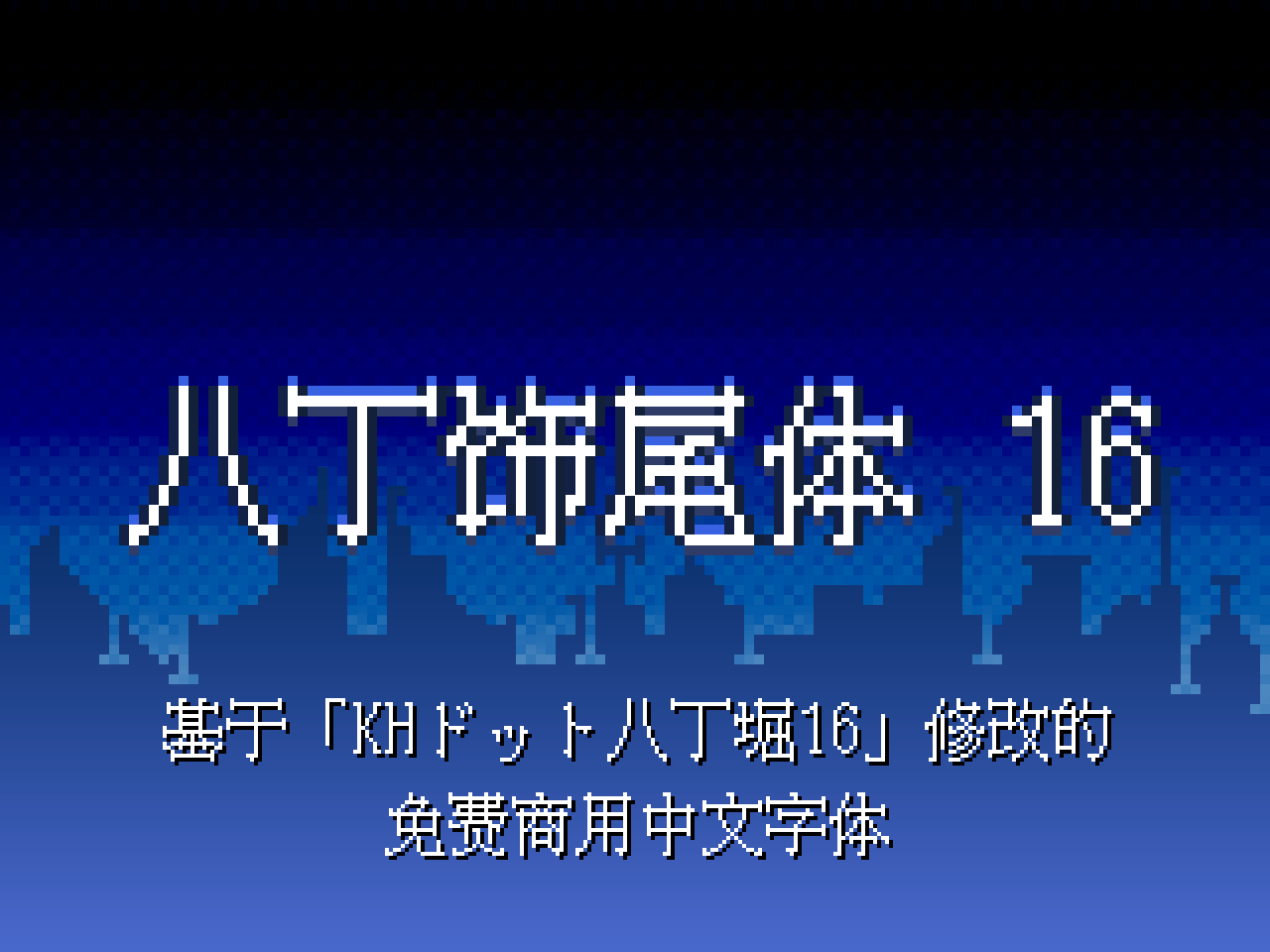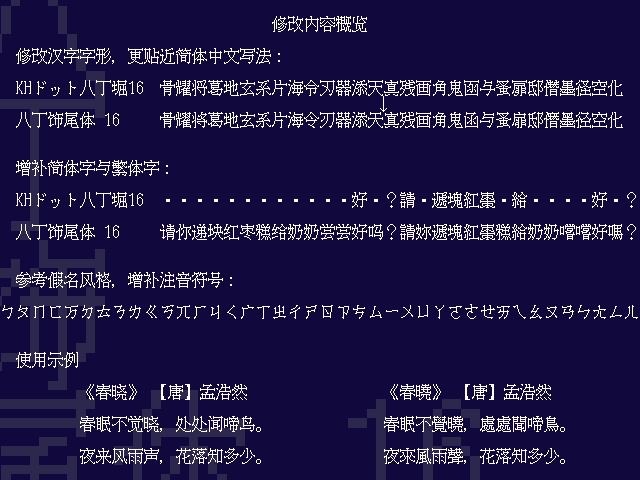
「八丁饰尾体 16」是一款点阵字体,它源自于「KHドットフォントシリーズ」系列中的「KHドット八丁堀16」。在此基础上,本项目对其字符集进行了重要扩展,增补了大量的简体与繁体中文汉字,使其能够满足中文语境下的排版与显示需求。作为一款16像素的字体,它非常适合用于像素风格(Pixel Art)的独立游戏、复古界面设计,以及那些需要营造科技感、电子感或数字美学的招牌与标题装饰中,为作品增添独特的视觉风格。尽管原字体在类型上被归类为「隶书体」,但在深入研究其汉字部分的笔画形态与结构特征后,项目团队发现其笔画末端的装饰性处理和整体的风格化倾向更为突出,因此最终决定采用「饰尾体」这一名称,以更精准地反映该字体的设计神韵与艺术定位。